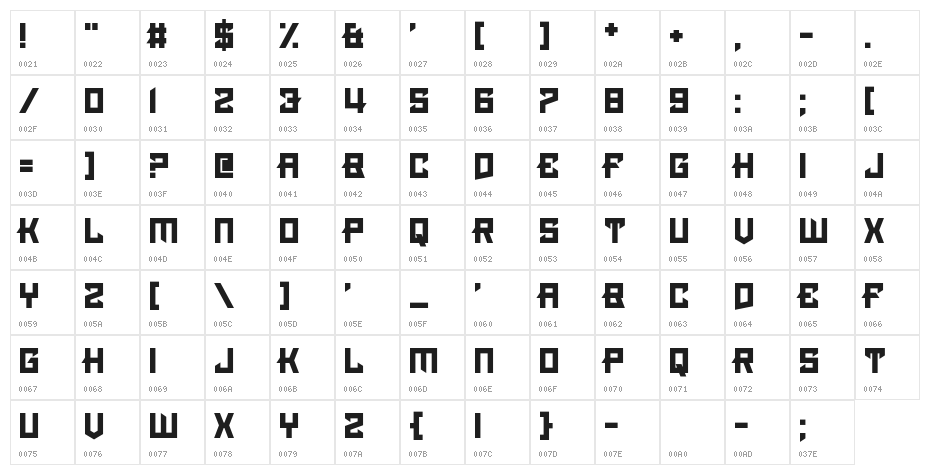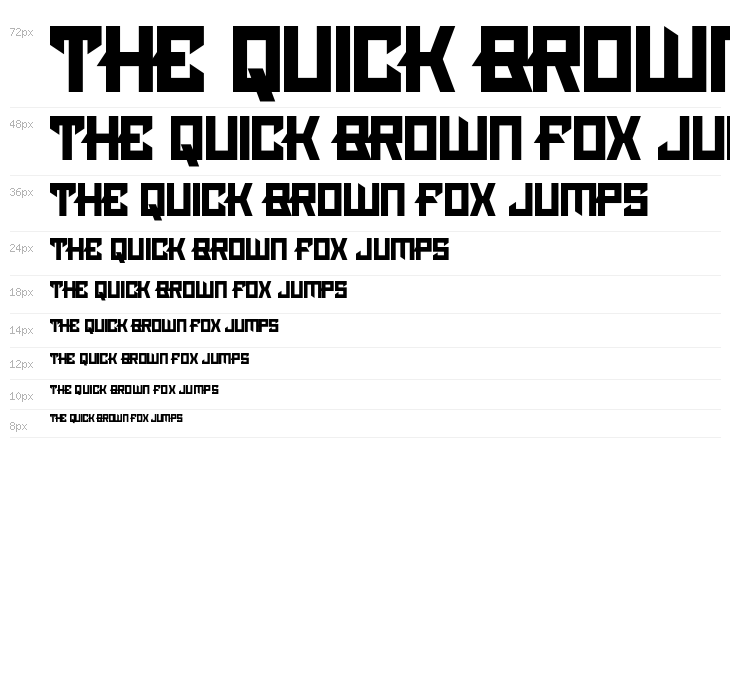
Pimlico Font
✎ Futuristic
| Vorgeschlagene Projekte | Ideal for branding, posters, video game titles, and any project requiring a modern, edgy look. |